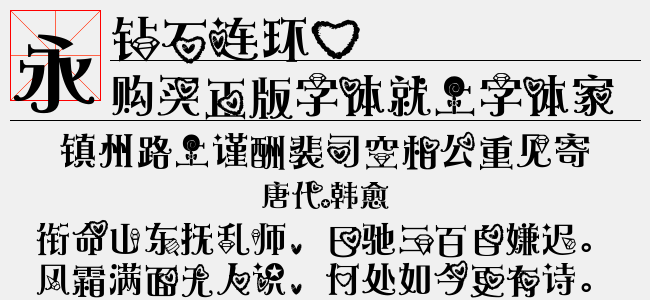
钻石连环心(12.53 MTTF中文字体下载)
钻石连环心 字体大小12.53 M,包含了6763个汉字以及附加其他英文字体和阿拉伯数字,属于佚名。钻石连环心(TTF)可以免费下载,商业用途请自行购买版权,它的特征就是创意,花体,卡通,装饰,采用安装嵌入的安装方式,支持符号拉丁文日文中文等语言
字体名称:钻石连环心